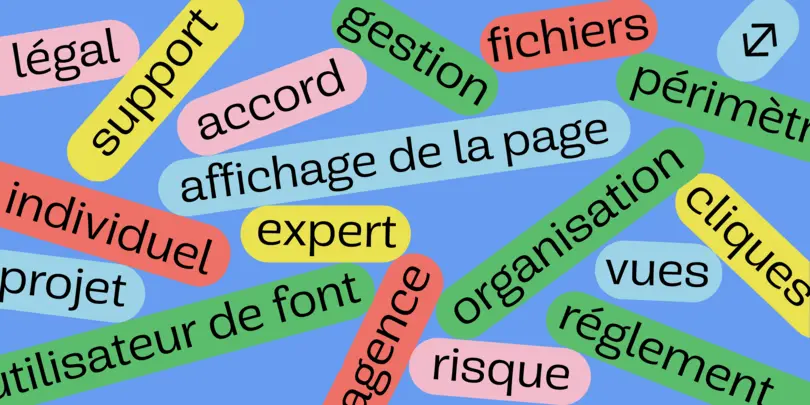
Licences de polices : comment éviter les pièges !
“ Countless organizations have released marketing materials, ads, campaigns, and new brands – only to find out too late that they have used the wrong font. Here's what happens and how to avoid it. ”
Polices de caractères. Musique. Images. Couleurs. Ces éléments font tous partie intégrante de la création de ressources numériques et des campagnes marketing. Mais comme la pantoufle de verre de Cendrillon, une seule et unique police peut convenir à un projet ou à une campagne spécifique et créer la magie. Si une équipe marketing ou de création trouve ce qu’elle pense être la police parfaite pour exprimer le message qui se cache derrière un projet, tout le reste semble se mettre en place d’un seul coup de baguette. Enfin… à l’exception de la licence légale de la police.
Imaginez qu’une équipe créative consacre des heures à créer une campagne attrayante, optimisée pour plusieurs canaux et surtout, unique sur le marché. Avec minutie, elle cherche et trouve la police parfaite pour ses objectifs et lance la campagne. Mais, une fois la campagne lancée, l’équipe juridique de l’entreprise reçoit un courrier d’une fonderie de polices de caractères. Cette lettre explique que leur campagne ou série à succès contient une police dont la licence n’a pas été correctement octroyée.
L’équipe juridique se retrouve à devoir élaborer un plan d’action. Elle communique sans relâche avec la fonderie, l’équipe créative, les dirigeants de l’entreprise et le service des relations publiques. Le budget doit maintenant prévoir une révision complète de la campagne, ainsi que les dommages et intérêts accordés à la fonderie. Les batailles juridiques sur les licences des polices de caractères sont source de mauvaise presse et de dépenses supplémentaires. La campagne, pourtant déjà lancée, doit finalement être retirée des plateformes physiques et numériques. En raison de l’absence de licence de police appropriée, les chefs de service doivent assumer la responsabilité de l’erreur et l’entreprise perd de l’argent.
Pourquoi investir dans une police de caractères ?
Les polices de caractères sont la clé d’une ​​bonne campagne marketing. Grâce à des polices spécifiques, des équipes de baseball américaines comme les Athletics d’Oakland ou les Washington Nationals se distinguent des autres équipes de baseball ou franchises sportives. Coca-Cola arbore une police originale qui se détache sur son fond rouge vif, tandis que Walt Disney a créé son propre logo avec un D enroulé. Au-delà des logos, les polices aident les marques à créer une identité claire avec leurs produits – pensez aux M&M’S. Et, même du point de vue de simples campagnes publicitaires, des projets tels que l’iconique « Got Milk? » aux États-Unis se sont construits sur des typographies claires, faciles à lire, qui offrent aux lettres un aspect distinctif.
Les entreprises qui font de la publicité ou qui s’appuient sur différentes plateformes doivent également prendre en compte les polices de caractères pour chaque support : certaines polices peuvent se démarquer sur Instagram, tandis qu’elles peuvent sembler encombrantes et poussives sur YouTube. D’autres polices se traduisent bien sur un panneau d’affichage, mais peuvent perdre beaucoup d’impact lorsqu’elles sont transposées au format numérique ou mobile. Pour réussir une campagne publicitaire ou un projet destiné à un public, les créatifs ont besoin de polices de caractères spécifiques pour transmettre leurs messages.
Les fonderies ont tout ce qu’il faut
Les fonderies, ou les entreprises qui créent des polices, distribuent ces polices conformément à des licences qui permettent aux utilisateurs de les utiliser de manière spécifique. Les licences commerciales s’appliquent aux campagnes marketing, aux ressources numériques publiques, aux publicités imprimées pour un journal ou un magazine, aux panneaux d’affichage, aux sites Web et aux applications. Les licences desktop peuvent être utilisées pour des projets plus personnels ou des événements internes, comme une fête de bureau ou une présentation PowerPoint lors d’une réunion interne.
Le Contrat de Licence Utilisateur Final, que les utilisateurs signent lorsqu’ils achètent une police de caractères ou tout autre type de logiciel, peut constituer un problème majeur avec l’octroi des licences de polices. Des centaines de milliers de polices existent en ligne. Et chacune d’entre elles est accompagnée d’un Contrat de Licence Utilisateur Final. Pour les services juridiques, ce sont des centaines d’heures consacrées à l’examen minutieux de chacune d’entre elles, afin d’éviter les poursuites en matière de droits d’auteur. Et si quelqu’un interprète mal les règles, les résultats peuvent être encore plus coûteux en heures de travail et autres procédures juridiques.
Le problème de la licence légale des polices : apprendre de ses erreurs
Les designers, les services juridiques et les dirigeants connaissent l’importance de mettre les points sur les i et les barres sur les t, et ce, quelle que soit la taille des caractères. Des documents marketing, des publicités, des campagnes et de nouvelles marques ont déjà été lancés par des acteurs industriels majeurs en utilisant la mauvaise police de caractères – et lorsqu’ils l’ont découvert, il était déjà trop tard.
Que se passe-t-il si vous utilisez une police de caractères sans licence ? Dans le cas des entreprises du secteur du divertissement, ces erreurs peuvent coûter des millions de dollars – et c’est sans parler du coût de la main-d’œuvre pour tout refaire, de l’argent gaspillé pour la publicité, etc. Quant aux marchandises dotées d’une police sans licence ou avec une licence incorrecte, elles doivent être retirées des rayons. Elles finissent reléguées dans une arrière-boutique pour ne plus jamais voir le jour.
Les designers ne sont pas les seuls à devoir faire face à ce genre de préoccupations. Selon le niveau de détournement, c’est un désastre en relations publiques qui peut se déployer et ravager la réputation d’une entreprise au passage. Récemment, une entreprise a fait les gros titres comme étant accusée de « vol de police de caractères », ce qui a suscité une association d’idées entre le terme « vol » et son nom de marque. Bien sûr, très peu de personnes ont la réelle intention de « voler » des polices de caractères. Mais les accusations publiées à leur encontre restent souvent gravées dans l’esprit de leur public ou dans les résultats des moteurs de recherche.
Conclusion